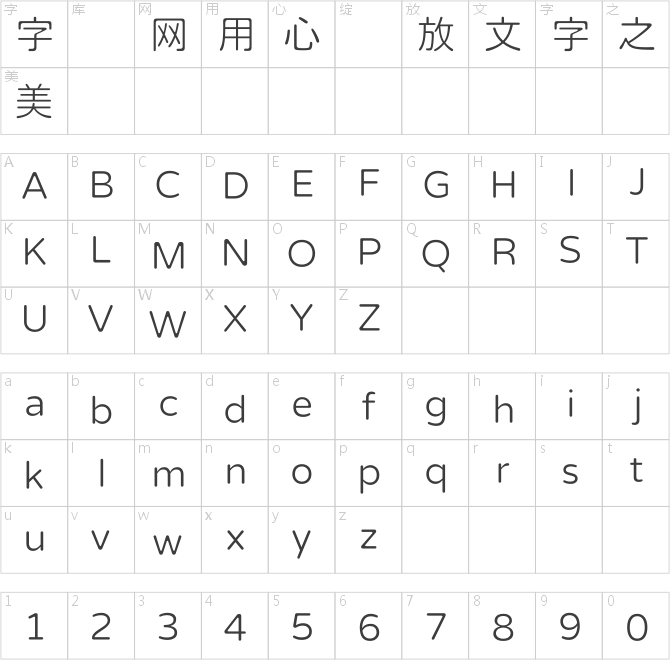
假粉圓体-ExtraLight
2020年3月14日,台湾JustFont.com公开了一款圆体字体“粉圆字体”给大家免费商用。由于现阶段可以免费商用的圆体字型十分少,所以这款字体十分受欢迎。而台湾的设计师Max,把这款字体调整增加了字体,使得这款字体具有5字重, ExtraLight,Light,Regular,Medium, SemiBold,更方便设计师使用了。而Max把调整过的字体命名为假粉圆体。
由于假粉圆体是通过程序自动进行调整的,所以有可能存在某些字因为笔画过粗而出现粘连,或者笔画过细而消失。所以大家在使用时请检查有没有出现这样的情况。如果有问题,可以向Max反映。